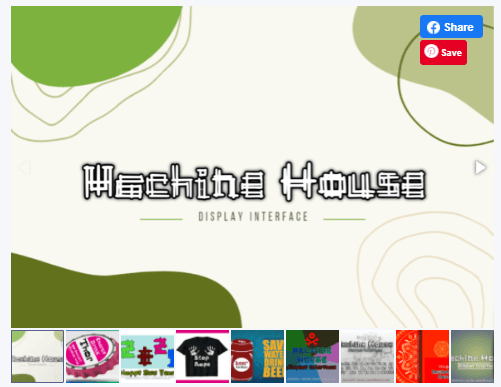
Machine House Font
Machine House - это игривый дисплейный шрифт с уникальным стилем. Добавьте этот шрифт в свои творческие идеи и обратите внимание, как он выделит их!